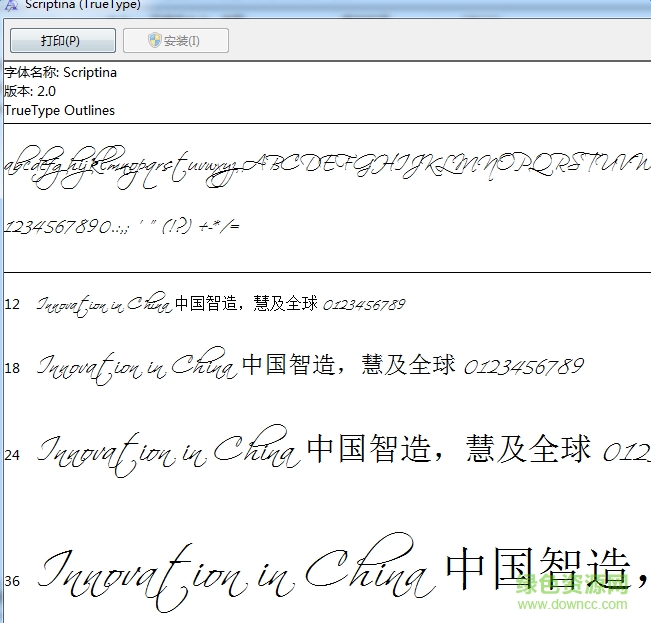
scriptina字體是一款英文字體庫(kù)中的個(gè)性字體,該字體可以廣泛應(yīng)用于美術(shù)設(shè)計(jì)、廣告設(shè)計(jì)、宣傳海報(bào)、ppt、影視制作以及任何使用文字的領(lǐng)域,有需要的朋友可以免費(fèi)下載收藏。
scriptina字體是一款極具個(gè)性的英文字體,該字體非常飄逸靈動(dòng),具有非常強(qiáng)的藝術(shù)效果。有喜歡的用戶趕快來(lái)綠色資源網(wǎng)下載使用吧!